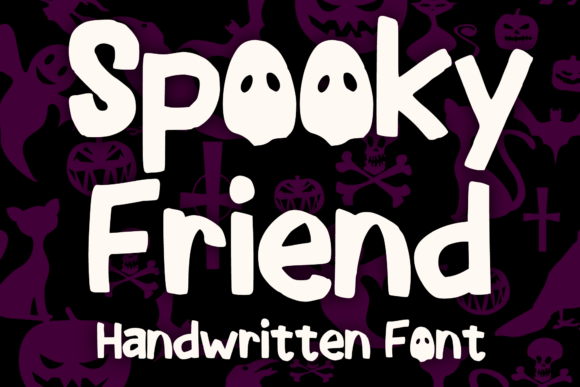
Spooky Friend
適切なデザイン要素を見つけるのは難しい場合がありますが、Spooky Friendは作品を即座に引き立てる優れたコレクションを提供します。
POD(オンデマンド印刷)製品、結婚式の招待状、またはソーシャルメディアのグラフィックを作成している場合でも、Spooky Friendは理想的です。